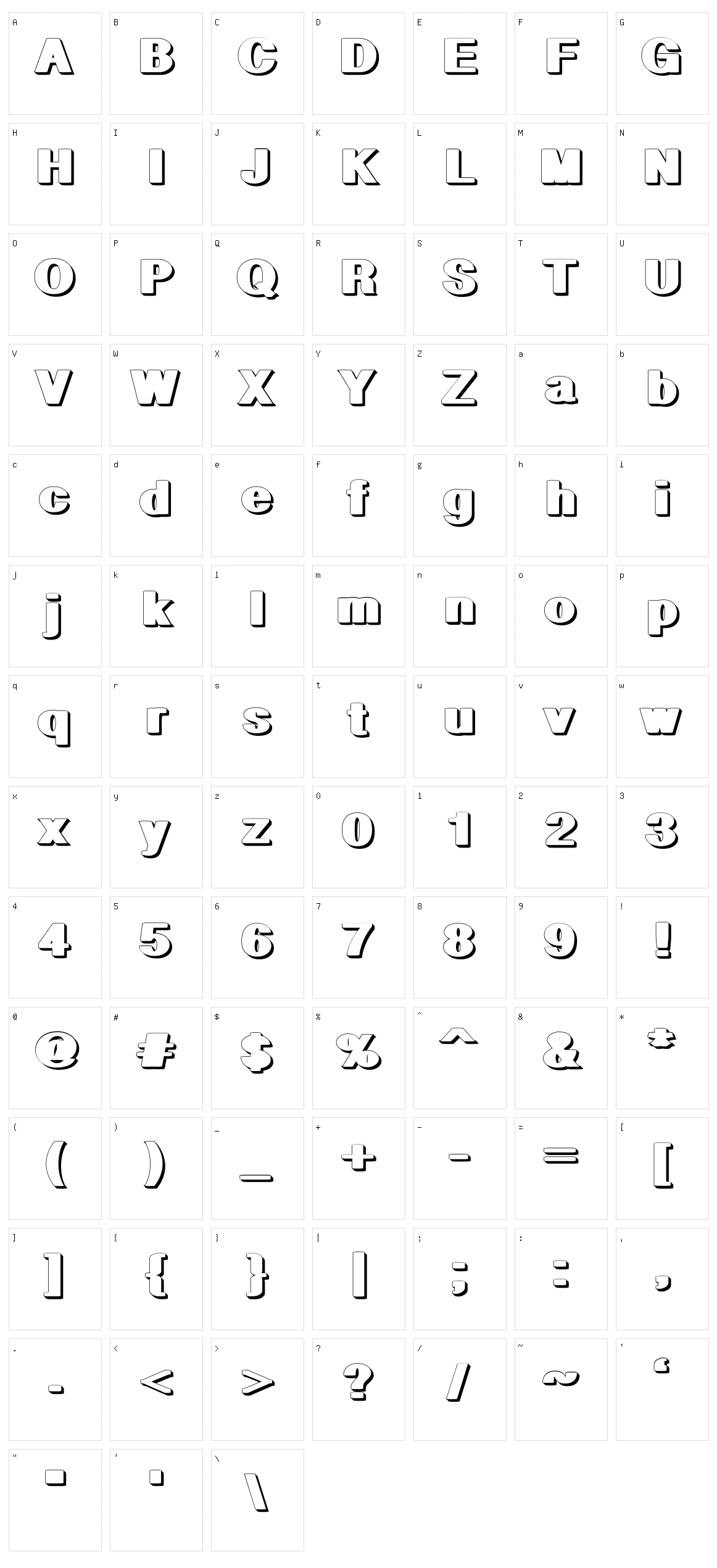
GEOMETRIC REGULAR SHADOW PW
o design mais tradicional que existe, a meu ver, para letras humanisticas. daí o nome. todavia justamente esta forma standardizada, e portanto altamente legivel e compreensivel como fonte torna-se base segura para uma serie de experiencias menos ortodoxas com as letras.
neste caso, sombreamento dos tipos seguido de um kerning apertadissimo traz um display pronto para uso em chamads publictárias, revistas e outras aplicacoes.
a familia geometric traz, portanto, uma serie de aplicacoes possiveis para uma mesma fonte tradicional.